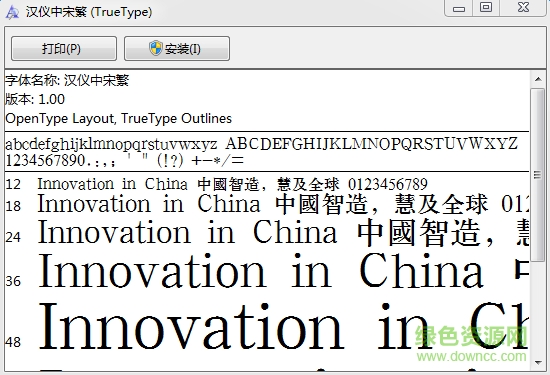
軟件介紹 軟件標簽: 漢儀字體 字體 漢儀中宋繁體是一款實用性很強的電腦繁體字體,這款字體寫出來的字很整齊,一筆一劃的,很是工整,很適合用于書本印刷方面,歡迎有需要的朋友來綠色資源網(wǎng)下載。安裝說明:第一種1.下載字體并解壓縮;2.開始中打開控制面板;3.在控制面板中打開字體文件夾;4.把下載的字體復制到此文件夾下;5.文字添加完成第二種1.下載字體并解壓縮;2.把文件根目錄下的字體壓縮包解壓縮;3.把文件根目錄下的安裝字體.bat放到含有字體文件的文件夾中,雙擊安裝字體.bat軟件;4.文字添加完成 本字體如果商用,請聯(lián)系漢儀字體官方獲得授權(quán)。 軟件截圖 上一張下一張(1 / 1) 安裝詳細截圖 其他版本下載 標題 大小 更新日期 下載 下載地址 電腦版 漢儀中宋繁體 點擊報錯 軟件無法下載或下載后無法使用,請點擊報錯,謝謝! 關閉報錯反饋 請描述您所遇到的錯誤,我們將盡快予以修正,謝謝! *必填項,請輸入內(nèi)容 本類最新 漢儀孟瑞體ttf v1.0 官方版 漢儀字庫免費 132款 阿里巴巴普惠字體 官方ttf版 漢儀字體打包大全 for Mac 蘋果電腦版_ 共131款字體 漢儀純愛情書拼音體 ttf版 漢儀北魏寫經(jīng)w字體 免費版 相關文章 Photoshop字體安裝使用方法和技巧 如何解決“無法新增字體”問題 Win 7系統(tǒng)安裝字體方法 網(wǎng)頁字體大小設置方法 怎么改網(wǎng)頁字體大小 在Linux系統(tǒng)中安裝字體的幾種方法 windows7字體顯示問題:打開某些程序的時候顯示的是亂碼 用戶評論 熱門評論 最新評論 發(fā)表評論 查看所有評論(0) 昵稱: 請不要評論無意義或臟話,我們所有評論會有人工審核. 字數(shù): 0/500 (您的評論需要經(jīng)過審核才能顯示)